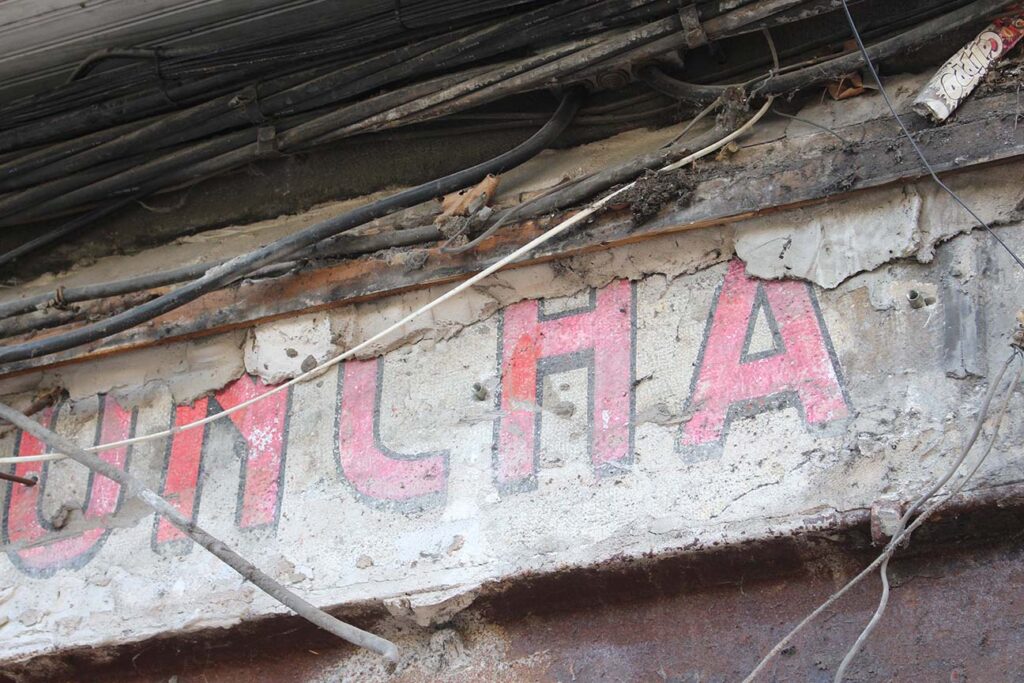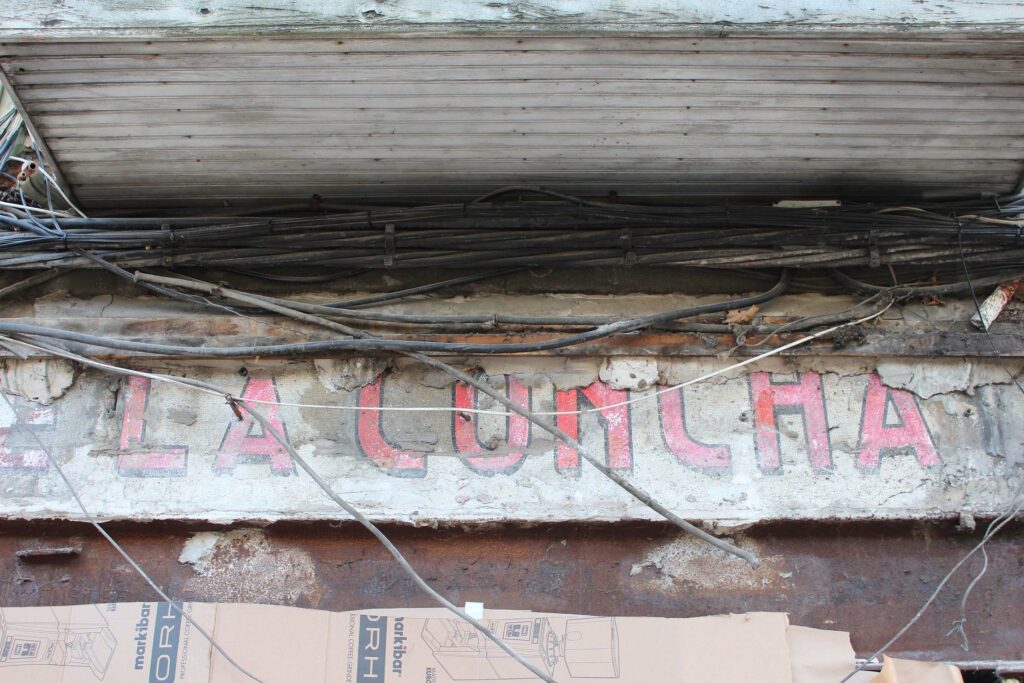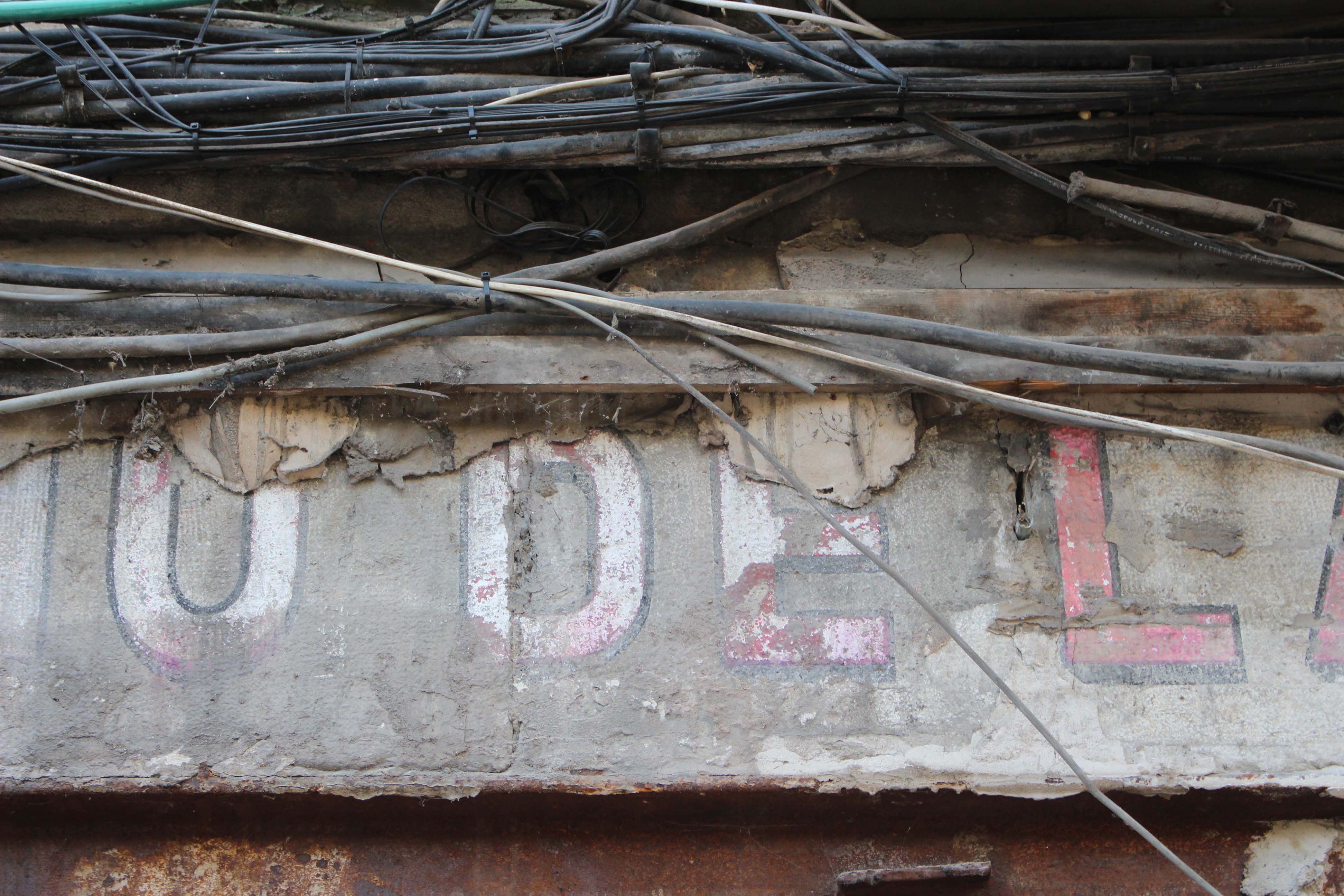
El Ultramarinos de Aquilino de la Concha
Con el inicio de las obras del local comercial ubicado en la calle Vargas, 9 de Santander, ha emergido el rótulo original del viejo comercio «Aquilino de la Concha. Ultramarinos».
Rotulación de mediados del siglo XX (entre los años 30 y 50) hecha sobre el dintel de la misma superficie de lo que fue la tienda, realizada en una tipografía de palo seco con tono rojo y negro. Hay una parte que está bastante más deteriorada la izquierda, pero otra que vemos perfectamente la calidad del trabajo y los pigmentos originales. Su conservación, probablemente, ha podido ser porque a la hora de instalar otros rótulos posteriormente, se hicieron sobre dos listones de madera para montaje, como se ve en los restos del que es el superior, lo que pudo generar esa cámara de aire.
Este local ha sido ocupado posteriormente por otros negocios, lo últimos y más conocidos desde comienzos del s.XXI han sido el Nilo’s, Pecados o La Ruta.
Fotos de Google Maps de los años: 2009,2016 y 2019 respectivamente.
Sobre Aqulino
Para conocer la historia de Aquilino, lanzamos la pregunta a las redes sociales y tuvimos la suerte de que nuestra amiga y custodia Carmen Toraya localizase la información que a continuación reproducimos:
D. AQUILINO DE LA CONCHA RUIZ, un jándalo de Llerena ( Cantabria), que de chicuco emigró a Cádiz, La Tacita de Plata, donde vivió muchos años dedicándose con esfuerzo al comercio de ultramarinos ( ver recorte que aporto, publicado en la prensa santanderina de comienzos de noviembre de 1935).
D. Aquilino tomó la decisión de regresar a su tierra y establecerse en la capital, eligiendo el local de la calle Vargas número 9, que ya funcionaría a finales de 1935/36. Sabemos también que nuestro tendero tenía carácter solidario, pues estando en Cádiz contribuyó a una cuestación popular para la creación de Cantinas Populares en las Escuelas Públicas y, ya en Santander, también aportó de su pecunio para sostener a las Milicias del Frente Popular.
Recién terminada la guerra civil en Santander, le fue concedido el 9/5/1938 por el Ayuntamiento de Santander, permiso para ampliar su negocio de comestibles y ultramarinos en el local que mencionamos de Vargas número 9, bajo.
Hemos indagado más y encontramos en 1953 a Los ULTRAMARINOS AQUILINO CONCHA, funcionando en su local de la calle Vargas. Asimismo, a finales de 1954 y 1955, felicitando a sus clientes los nuevos años 1955 y 1956 ( ver en Comentarios), y en 1966, demostrando toda una trayectoria laboral en Cádiz y Santander.